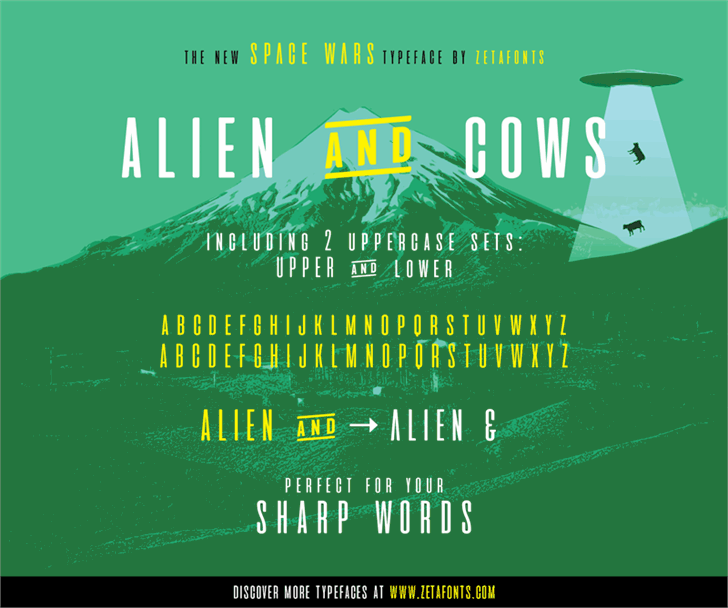
Aliens And Cows Font
Aliens And Cows é uma elegante fonte sans serif do designer Francesco Canovaro. Com uma densidade ultracondensada, esta fonte exibe um conjunto de caracteres estendido que fornece suporte para várias línguas europeias, além de alternativas contextualizadas para alguns caracteres. Ideal para projetos de design gráfico que valorizam a simplicidade e modernidade, essa fonte é uma escolha incrível para qualquer projeto exigente, seja ele um site elegante ou um brochura publicitária criativa. Inspirada em sua inspiração futurista, Aliens And Cows é uma fonte divertida e versátil que combina elementos de alienígena com a natureza dos vacas, oferecendo um toque único que certamente fará sua marca brilhar. Esta fonte tem o poder de transformar qualquer projeto em algo realmente especial. Se você busca uma fonte para dar vida à sua ideia, Aliens And Cows é definitivamente um produto a ser considerado.